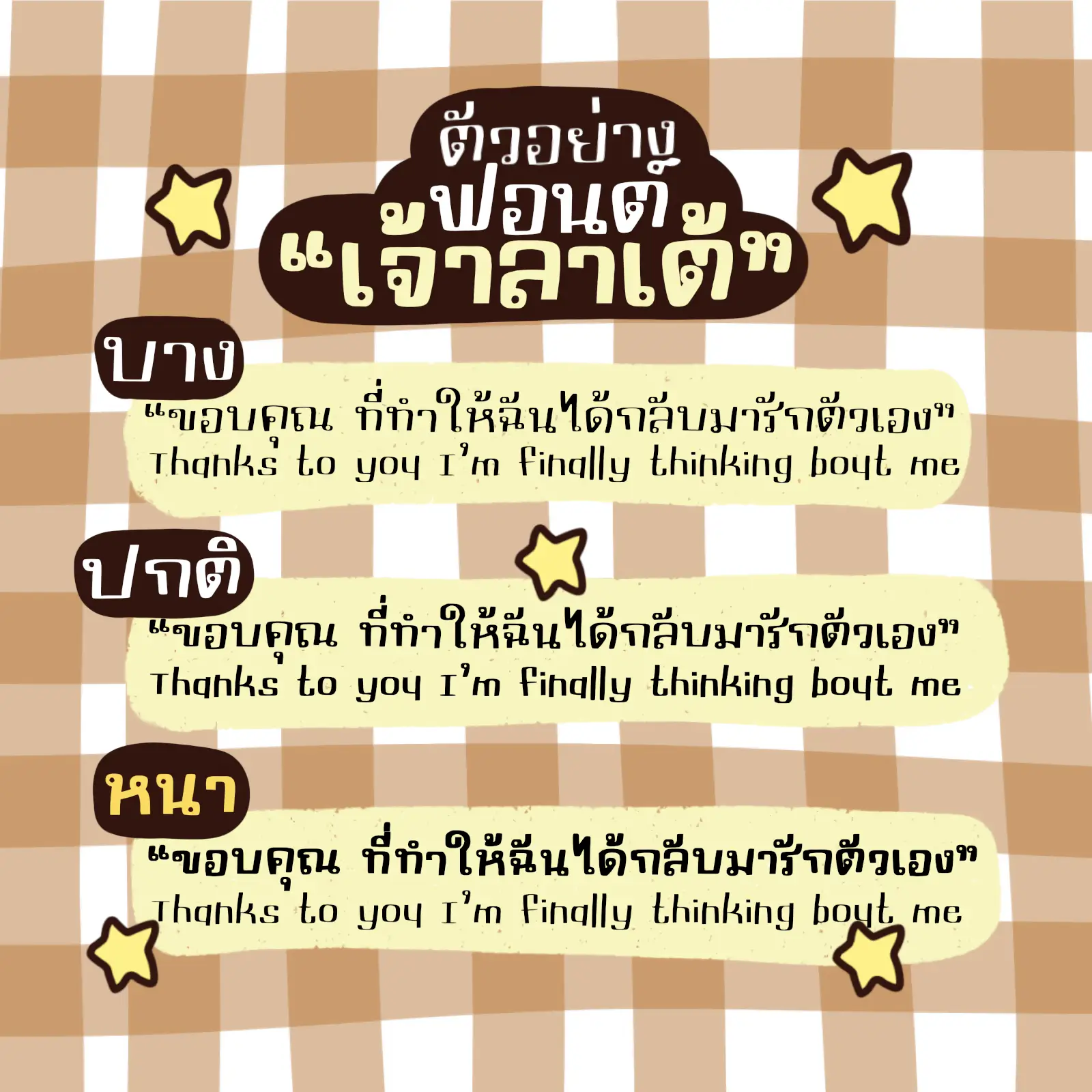
แจกให้ใช้งานฟรี สำหรับน้องๆพี่ๆ ที่ชอบฟอนต์ลายมือตัวเหลี่ยมๆ อ่านง่าย มีเอกลักษณ์น่าสนใจ
แนะนำว่านำไปใช้งานกับการจดเนื้อหา สรุปงาน จดโน้ต จดบันทึก เป็นลายมือโคตรจะเท่เลย หรือจะนำไปทำคลิป แต่งรูป ก็เริ่ดสุดๆ อ่านไม่ยาก ถูกใจวัยรุ่น มีติดเครื่องไว้เลย แนะนำสุดๆ
- มี 3 ขนาด (เส้นหนา / เส้นบาง / เส้นปกติ)
เจ้าลาเต้ (JaoLatte)